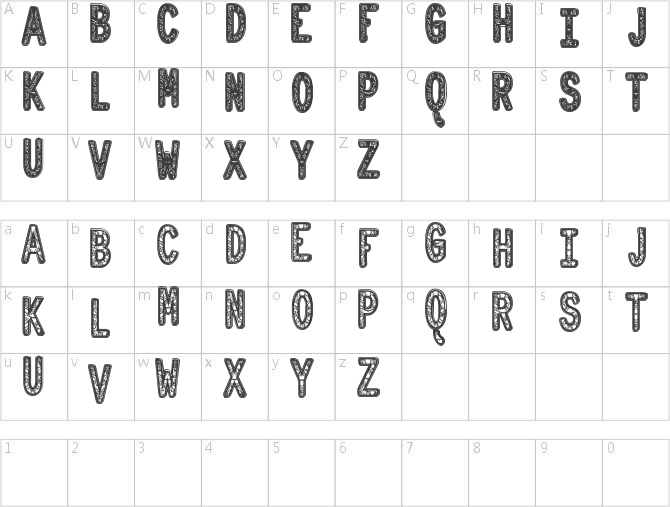
ORNAD dentro tfb 詳情頁(yè)
ORNAD dentro tfb字體字庫(kù)是一款讓人賞心悅目、百看不厭的英文字體,適合各類(lèi)廣告和產(chǎn)品包裝設(shè)計(jì)應(yīng)用,字體大小0.27MB,格式為ttf字體,上傳用戶(hù)是Apple,作者/版權(quán)方為未知